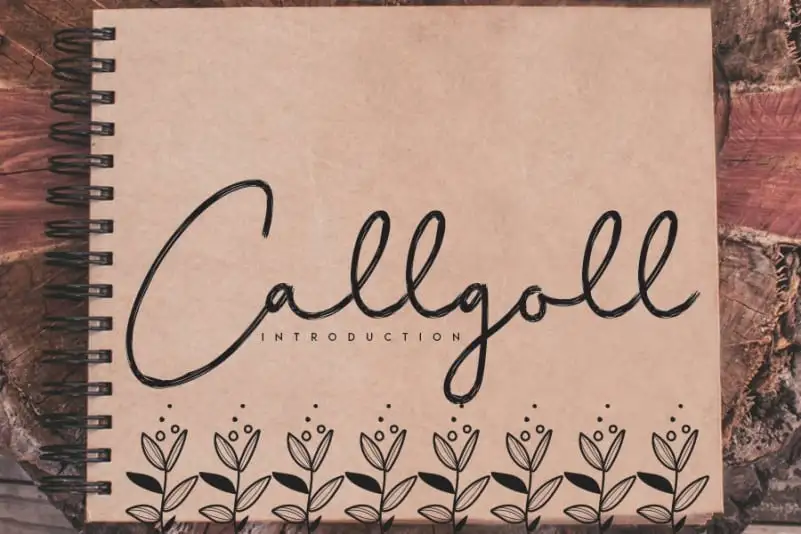
Callgoll Handwritten Font – Download Grátis
A Callgoll Handwritten Font é uma seleção única de letras cursivas criada com a ajuda de um pincel, resultando em um estilo casual e encantador que combina frescor e um toque acintosamente peculiar. Essa fonte perfeita para todos os seus projetos de logomarca, marcas identitárias, redes sociais, e até mesmo suas DIY criativas está disponível no formato Brush Fonts. Idealmente adaptada para quem busca personalidade e originalidade em sua marca ou projeto visual, a Callgoll Handwritten Font é uma escolha segura para aquelas pessoas que valorizam um toque delicado e divertido na linguagem do design gráfico.